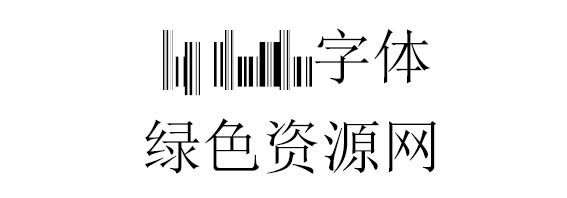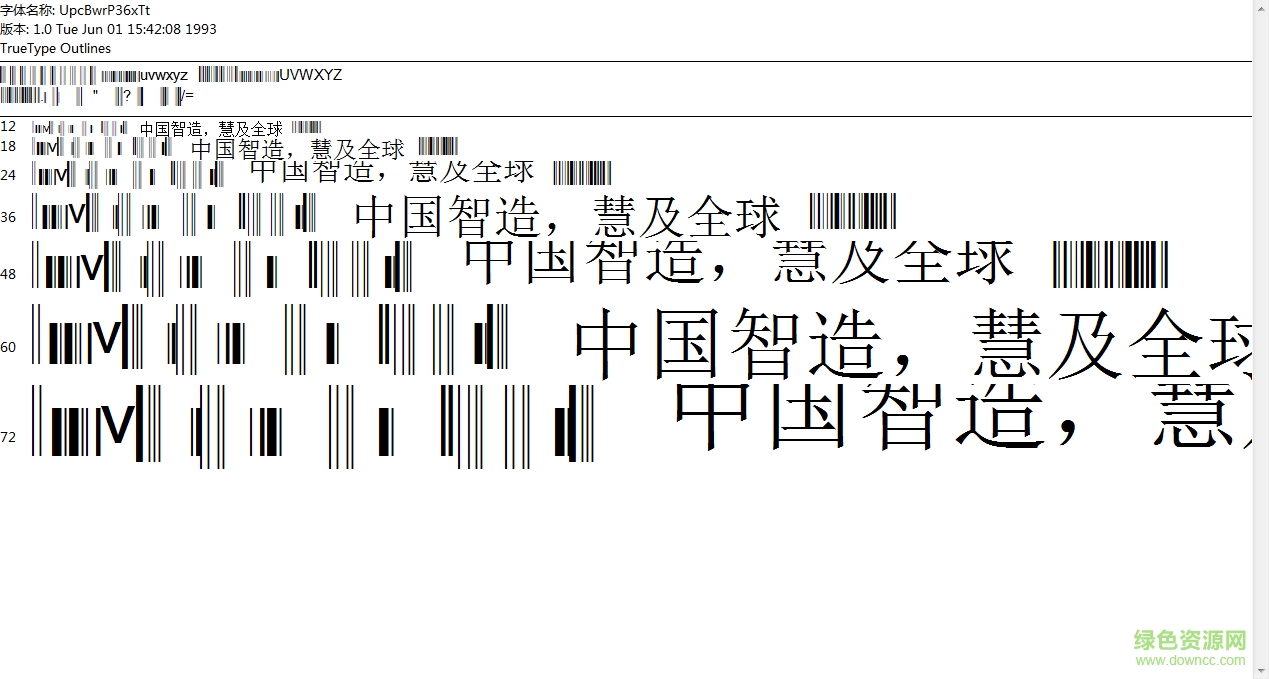
UpcBwrP36xTt是一款用戶條形碼設(shè)計(jì)方面的字體,一般可用于包裝印刷、屏幕設(shè)計(jì)、廣告創(chuàng)意等,整體效果非常出眾,需要的朋友來綠色資源網(wǎng)下載!
UpcBwrP36xTt字體是一款非常好看的條形碼文字,呈現(xiàn)的線條高高低低的,給人帶哦來一種美觀